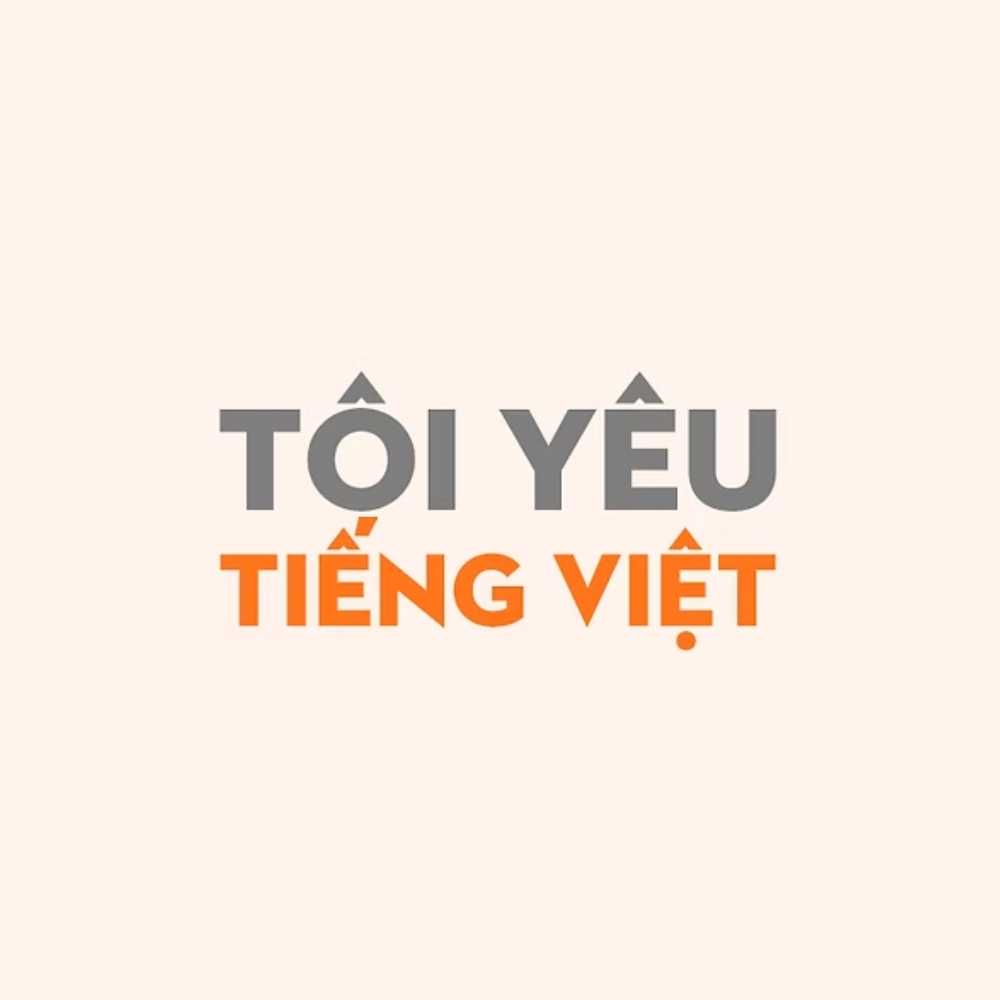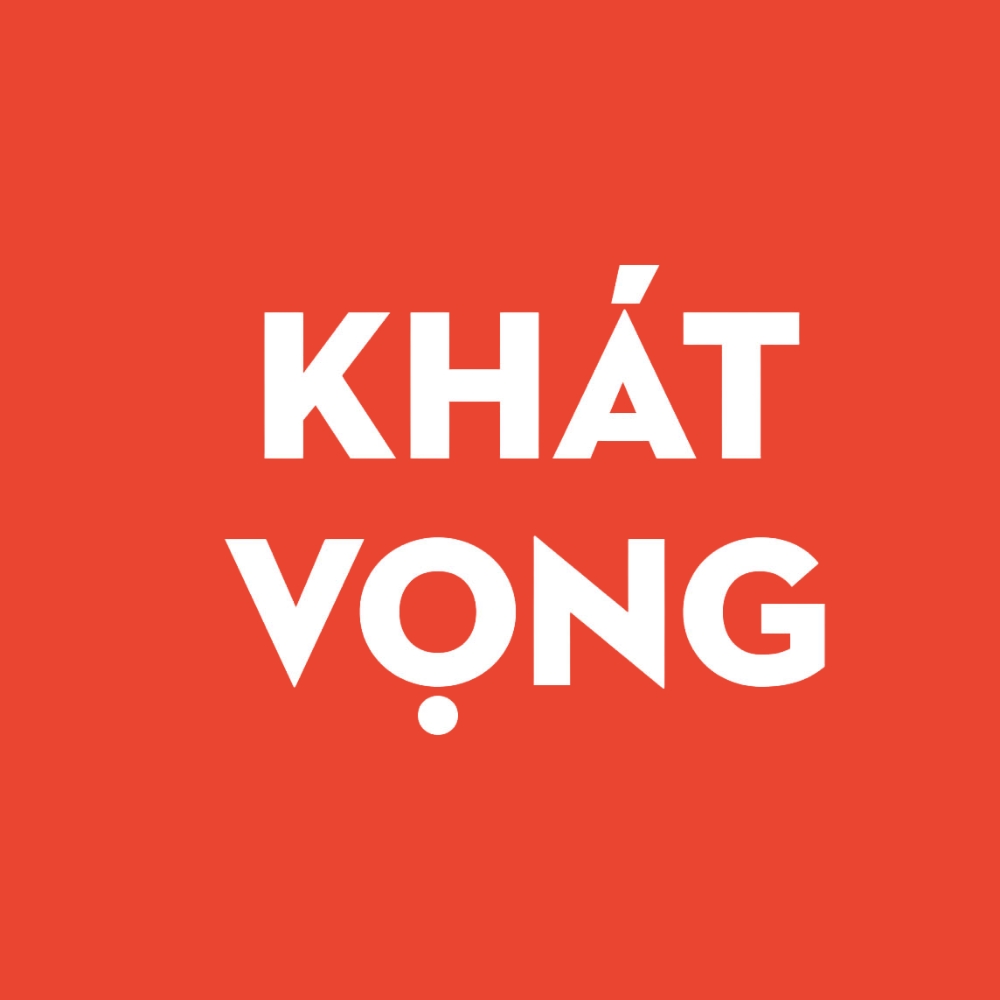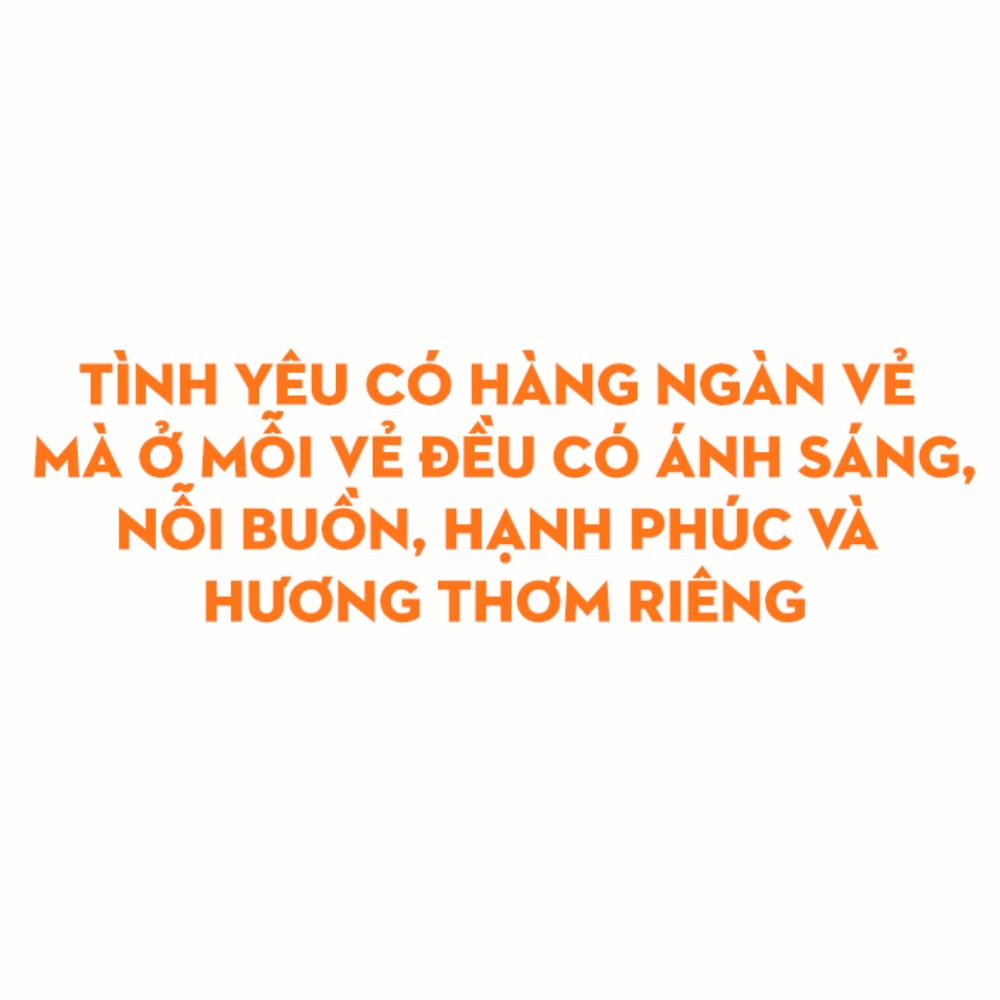
Nhiều designer chuyên nghiệp khi tìm kiếm font Việt hóa SVN-Neutraface 2 thường gặp tình trạng tải về nhưng các ký tự tiếng Việt có dấu như “ế, ồ, ử” bị lỗi hiển thị, lệch vị trí dấu thanh hoặc file chỉ là dạng bitmap PNG giả vector không thể phóng to.
Font Việt hóa SVN-Neutraface 2 là gì?
SVN-Neutraface 2 là một bộ font chữ thuộc phong cách Geometric Sans-serif (không chân hình học) mang tính biểu tượng cao trong giới kiến trúc và thiết kế hiện đại. Đây là phiên bản được phát triển dựa trên những nguyên tắc thiết kế của Richard Neutra – một trong những kiến trúc sư có sức ảnh hưởng lớn nhất thế kỷ 20.
Bản Việt hóa SVN đã khéo léo xử lý hệ thống dấu thanh tiếng Việt để hòa hợp hoàn hảo với các đường nét hình học sắc sảo, giúp font chữ này trở nên gần gũi và dễ ứng dụng tại thị trường Việt Nam.
Vì sao được sử dụng trong thiết kế và in ấn?
Lý do font Việt hóa SVN-Neutraface 2 được săn đón trong ngành in ấn bao bì nằm ở sự cân bằng tuyệt đối giữa nét thẳng và đường cong. Với cấu trúc dựa trên các khối cơ bản như hình tròn và hình vuông, Neutraface 2 mang lại cảm giác vững chãi nhưng không hề thô cứng.
Font chữ này sở hữu nhiều trọng lượng từ mảnh (Light) đến dày (Bold), cho phép nhà thiết kế dễ dàng phân cấp thông tin trên các ấn phẩm quảng cáo. Đặc biệt, nhờ độ tương phản nét thấp, font chữ này giữ được độ hiển thị cực tốt khi in ấn trên các bề mặt khó như kim loại, da thuộc hoặc thủy tinh cao cấp.
Trong thiết kế thương hiệu, Neutraface 2 đại diện cho sự tối giản, sang trọng và tầm nhìn xa trông rộng. Nó không chỉ đơn thuần là phương tiện truyền tải thông tin mà còn là một yếu tố định vị đẳng cấp. Các tập đoàn lớn, ngân hàng hay đơn vị kinh doanh bất động sản thường ưu tiên font chữ này để in ấn profile, bảng hiệu và quà tặng đối ngoại nhằm khẳng định vị thế và uy tín của mình.
Ứng dụng font Việt hóa SVN-Neutraface 2 trong thiết kế và in ấn
Nhờ đặc tính hình học chuẩn mực, SVN Neutraface 2 xuất hiện trong rất nhiều hạng mục sản xuất tại In Viva, từ bao bì cao cấp đến quà tặng công nghệ.
- Sản xuất bao bì hộp cứng sang trọng: Font chữ này thường được sử dụng để in logo hoặc tên sản phẩm trên các mẫu hộp nam châm, hộp âm dương đựng yến sào, rượu vang hoặc mỹ phẩm đắt tiền. Sự tinh giản của font chữ giúp bao bì trông gọn gàng và hiện đại hơn.
- In ấn profile và báo cáo thường niên: Các doanh nghiệp lớn thường chọn Neutraface 2 cho các tiêu đề lớn để tạo sự tin cậy và chuyên nghiệp trong mắt đối tác và cổ đông.
- Khắc laser quà tặng doanh nghiệp: Do có đường nét dứt khoát, font chữ này cực kỳ phù hợp để khắc trên bình giữ nhiệt kim loại, bút ký gỗ hoặc sạc dự phòng vỏ nhôm. Các nét khắc sẽ trở nên tinh xảo, không bị dính nét hay mờ nhòe.
- Thiết kế tem nhãn sản phẩm: Với phiên bản Light, Neutraface 2 giúp các thông tin chi tiết trên tem nhãn mỹ phẩm, dược phẩm trở nên rõ ràng, dễ đọc dù in ở kích thước siêu nhỏ.
Bộ font Việt hóa SVN-Neutraface 2 chính là chìa khóa để nâng tầm thẩm mỹ cho các dự án thiết kế và in ấn bao bì hiện đại. Với đường nét hình học sắc sảo và tính ứng dụng đa dạng, font chữ này sẽ giúp thương hiệu của bạn trở nên sang trọng và đẳng cấp hơn trong mắt khách hàng.